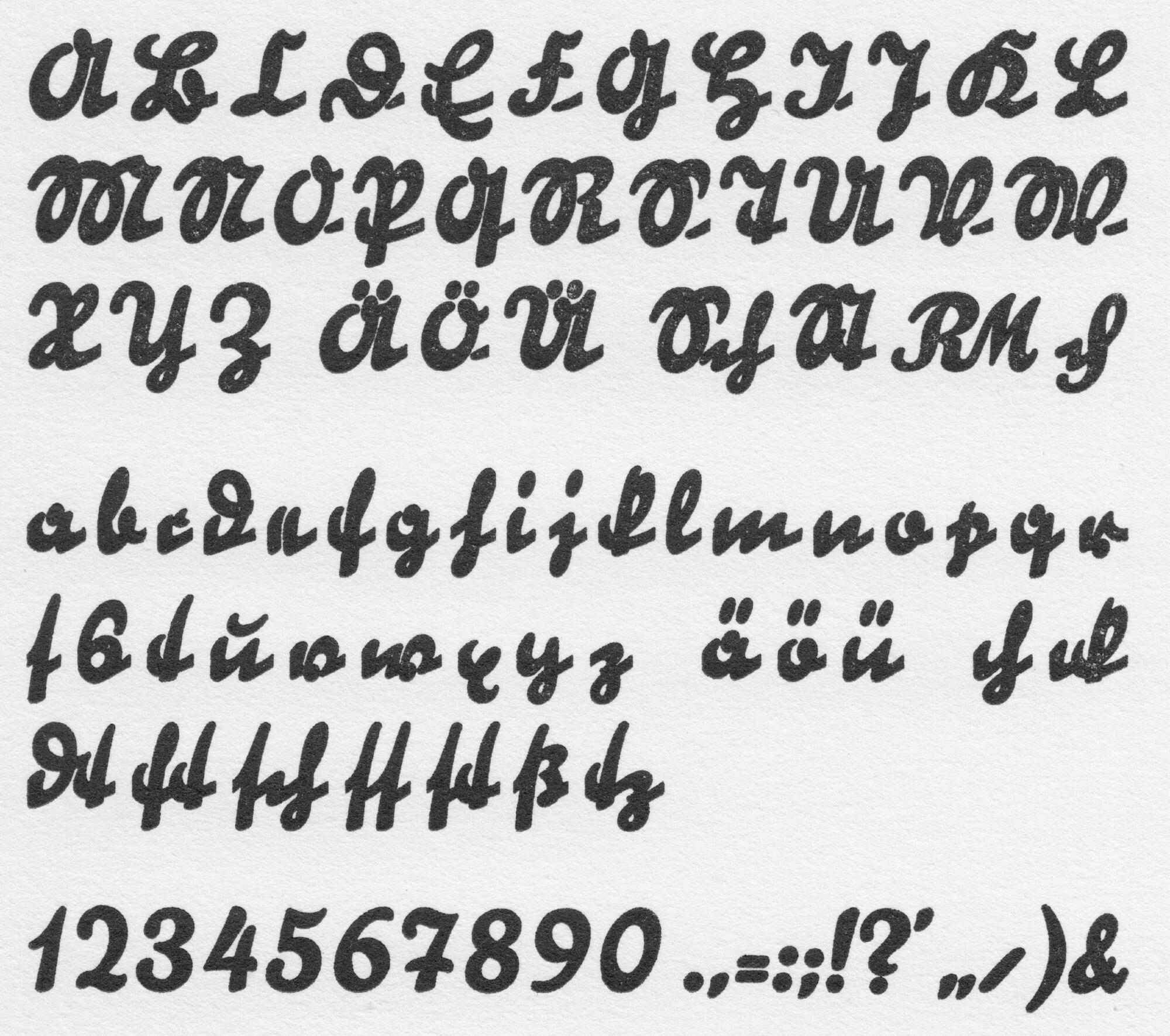
- 1934
- Gebrochene Schrift
Eine Schreibschrift von Theodor Paul Etbauer, erschienen 1934 bei der D. Stempel AG in einem mageren und einen halbfetten Schnitt.